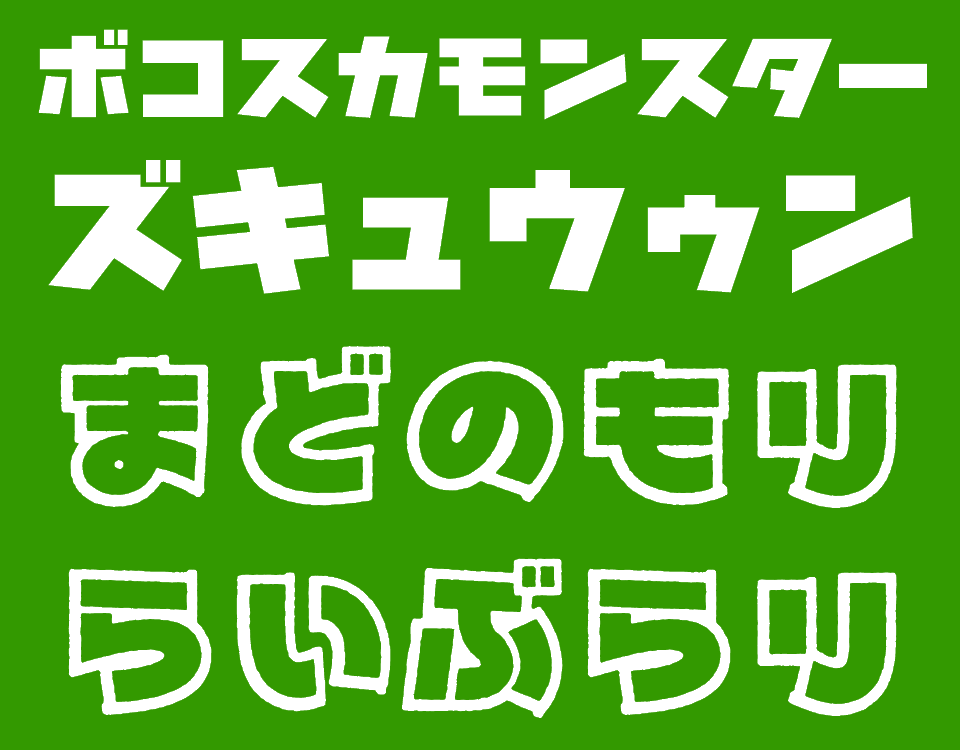
ゆるかわな擬音・擬態語を描ける極太な仮名フォント「ボコスカモンスター」
ギャグ要素が濃いマンガやアニメに最適、白抜き版も同梱
「ボコスカモンスター」は、ゆるい手書き感が魅力な極太フォント。ひらがなとカタカナのみを収録し、白抜き版も同梱されている。
極太な画線は目一杯に詰まりながらも重い印象がなく、直線的なカタカナではむしろキレも感じさせる。そのデフォルメされた文字は、ギャグ要素が濃いマンガやアニメのタイトル、もしくは擬音語や擬態語などの“描き文字”に最適だろう。
作者によれば、バトル系の作品を想定しているとのこと。比較的万能なデザインのカタカナはリアルな描写にもマッチする一方、ゆるさが強調されたひらがなは二頭身キャラが登場するような作品で活用したい。